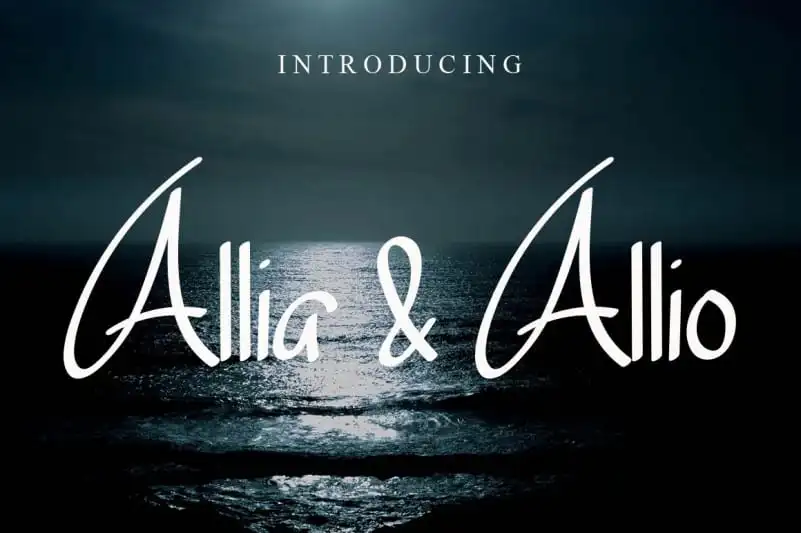
Allia & Allio Font
Allia & Allio é uma fonte escrita a mão que transmite relaxamento e frescura. Suas características naturais e únicas a tornam perfeita para diversas aplicações de design, oferecendo uma variedade infinita de possibilidades. Com esse tipo especializado em escrita a mão, você pode explorar seu potencial máximo, seja para criar cartões de presentes, calendários ou até mesmo gráficos empresariais com um toque pessoal e único. Esse é o perfeito exemplo da fonte ideal para quem valoriza uma autenticidade que traz empatia e conexão em suas criações.